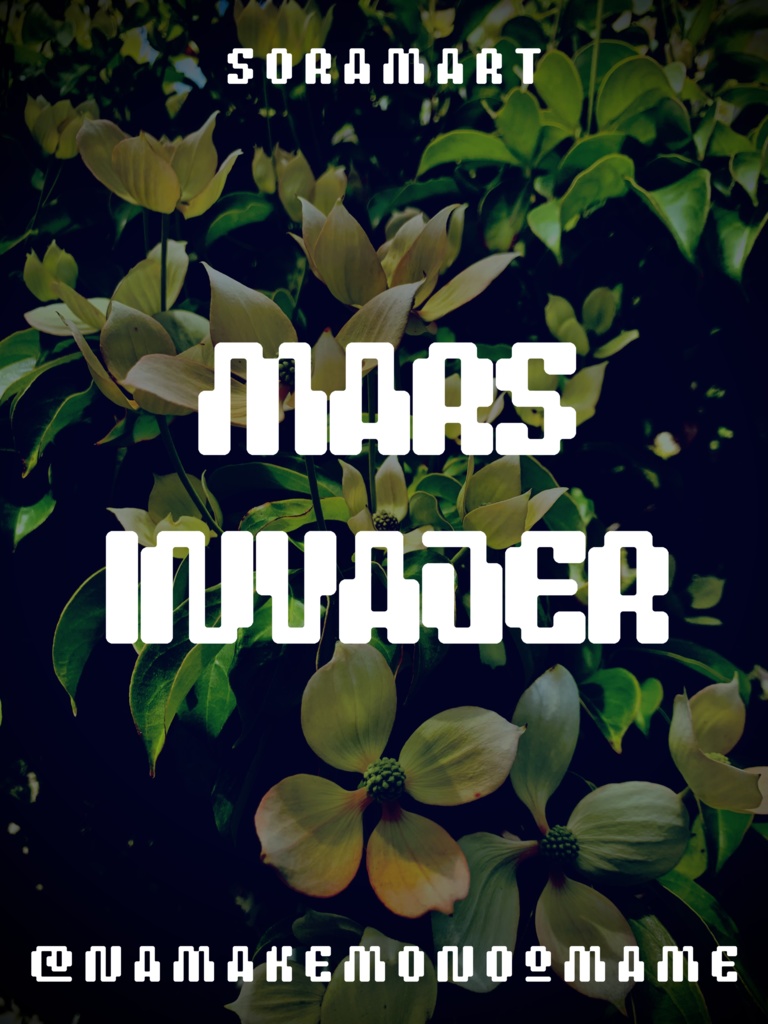
そらマートフォントデータ”Mars Invader”Digital2,500 JPY카트에 담기기프트 보내기About Giftレトロフューチャーなゲーミング・ポップフォント "Mars Invader" です。 「TrueTypeフォントファイル」という形式です。 ダウンロードした後、Zipファイル内のデータをインストールしてお使いください。 このフォントは商用利用可となっております。 お客様の制作・創作活動のお役に立てれば幸いです。 ※使用上の注意事項などは、添付のReadmeをお読みください。そらマートVisit FANBOX!Fontsフォントデータ”Crushed Can Serif Empty”そらマート200 JPYFontsフォントデータ”Crushed Can Serif Wide”そらマート0 JPYFontsフォントデータ”Crushed Can Serif”そらマート0 JPYFontsフォントデータ”Dolce Cube Tall”そらマート0 JPYFontsフォントデータ”Dolce Cube”そらマート0 JPYFontsフォントデータ”Eight-bit Quest Wide”そらマート2,500 JPYFontsフォントデータ”Eight-bit Quest”そらマート2,500 JPYFontsフォントデータ”Tonik Crate”そらマート2,500 JPYFontsフォントデータ”Vapor Sprout Edge”そらマート2,500 JPYFontsフォントデータ”Vapor Sprout Wide”そらマート2,500 JPYFontsフォントデータ”Vapor Sprout”そらマート2,500 JPYFontsフォントデータ”Star Shoot Ray”そらマート2,500 JPYFontsフォントデータ”Star Shoot Black Wide”そらマート2,500 JPYFontsフォントデータ”Star Shoot Black”そらマート2,500 JPYFontsフォントデータ”Mars Invader Balloon”そらマート2,500 JPYFontsフォントデータ”Mars Invader Wide”そらマート2,500 JPYFontsフォントデータ”Rock Cut Serif”そらマート2,500 JPYFontsフォントデータ”Rock Cut Drop Wide”そらマート2,500 JPYFontsフォントデータ”Rock Cut Drop”そらマート2,500 JPYFontsフォントデータ”Longtail Sans Serif Slashed”そらマート2,500 JPY더보기